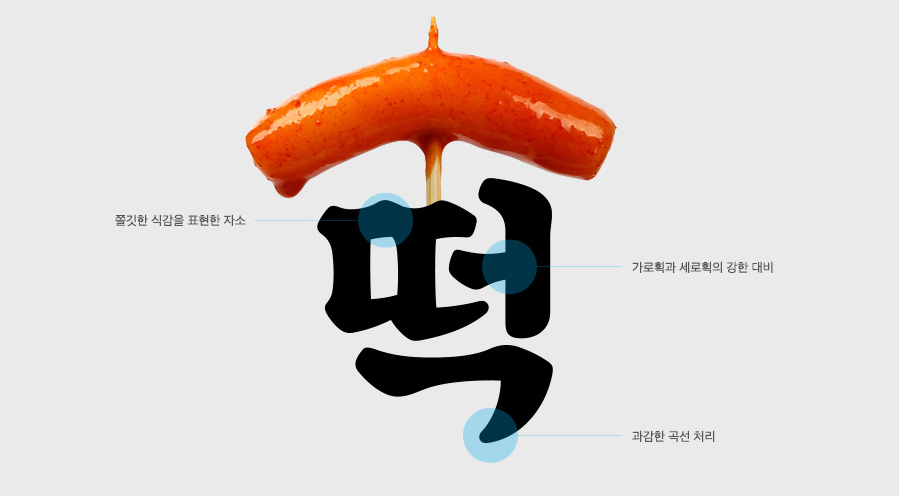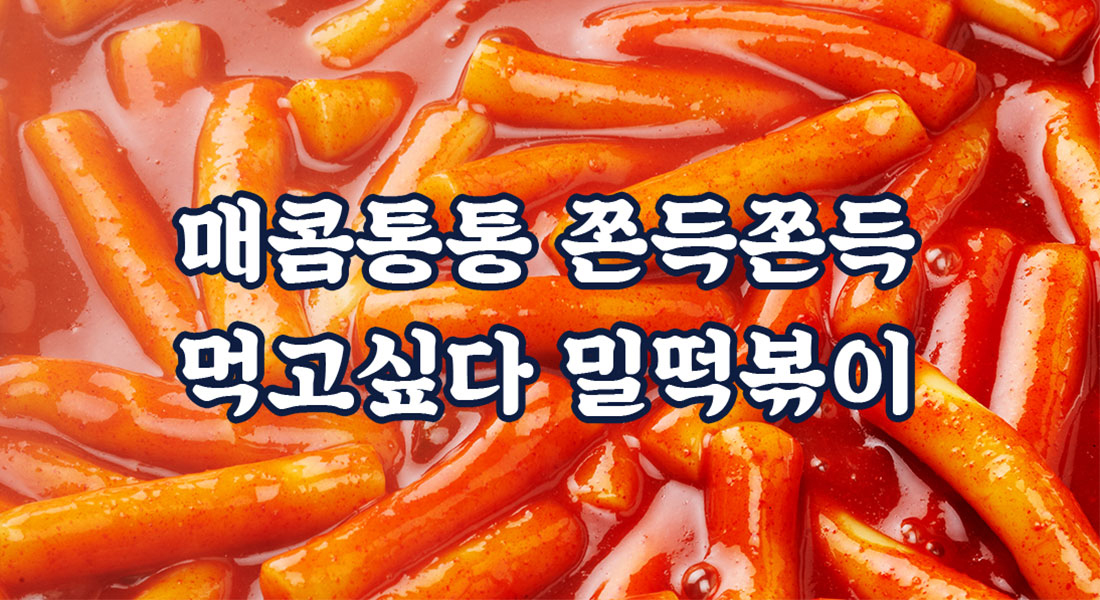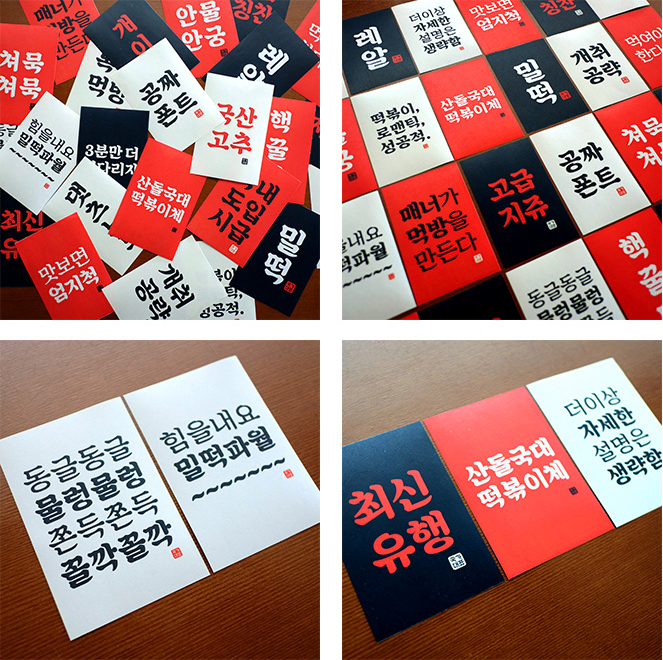
쫄깃한 떡볶이를 닮은 ‘Sandoll 국대떡볶이’
폰트 디자인 기업 산돌커뮤니케이션은 대표적인 프랜차이즈 브랜드 국대떡볶이와 함께 떡볶이를 모티브로 한 신규 폰트 Sandoll 국대떡볶이를 출시했다.
9월 신규 폰트 Sandoll 국대떡볶이는 붓으로 쓴 두꺼운 글자를 모티브로, 도구의 손맛과 질감을 재해석하고 밀떡 특유의 쫄깃쫄깃한 필감이 표현된 폰트이다. 명조서체의 진지함을 가지고 있으면서도 둥글둥글한 형태와 강한 획의 대비로 유머러스하면서도 친근한 느낌을 살려 재미있게 사용 할 수 있다.